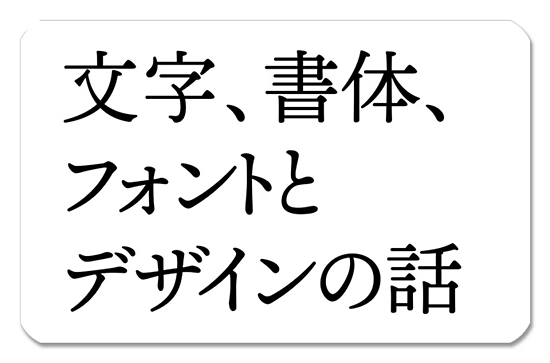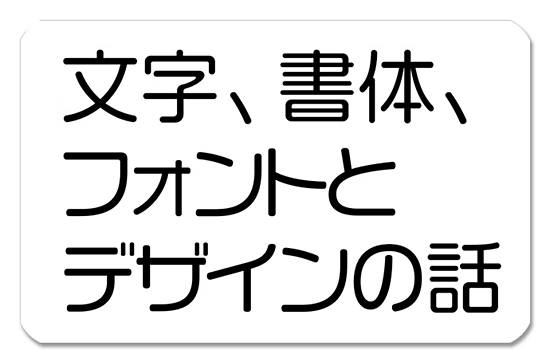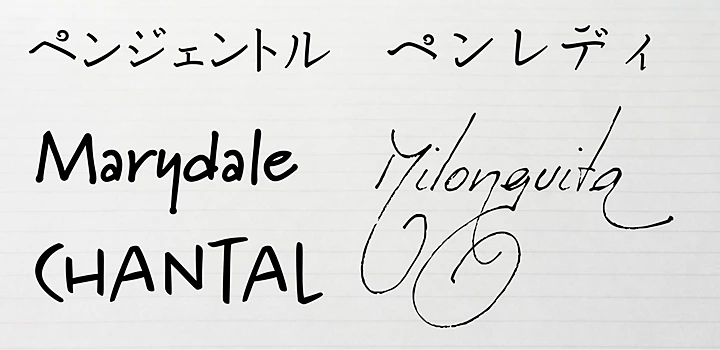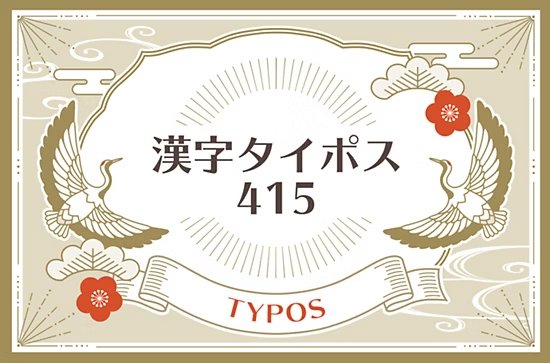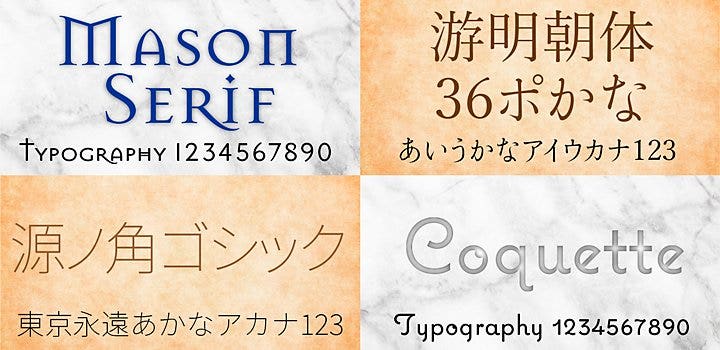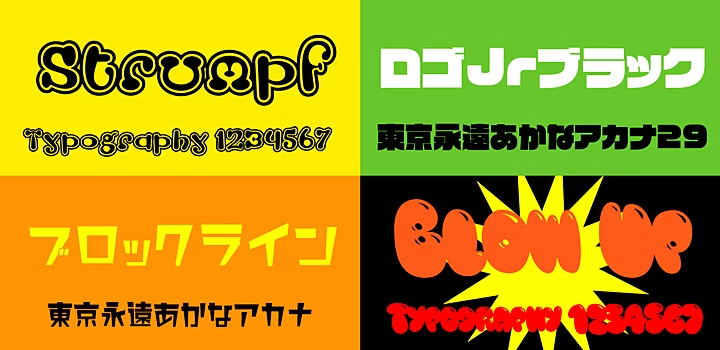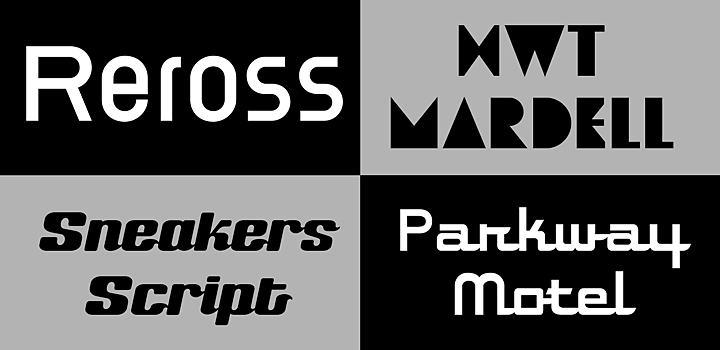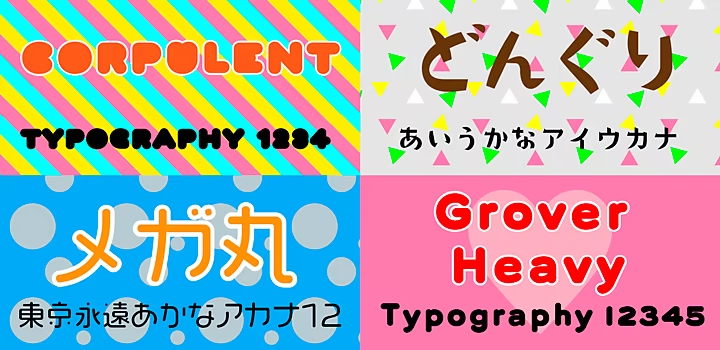
デザインイメージで決める!Adobe Fontsのおすすめフォント
たとえば同じ「あ」の文字でも、そのかたちとデザインはフォントによって大きく変わります。
デザインをする際には、かわいいデザインにしたい、かっこいいデザインに仕上げたいと言ったイメージや、伝える目的にあったフォントを選択し、レイアウトをしていくことが大切です。
ここではフォントによってデザインに与えるイメージはどう変わるのか、目指すデザインイメージを表現するためにはどんなフォントが最適なのかをご紹介します。
フォントはデザインイメージを決める大事な要素
デザインのイメージは、文字、写真・イラスト、レイアウト、配色等さまざまな要素が絡み合って作られていきます。
なかでも文字は情報を伝えるという大きな役割を持っているため、読みやすさ、見やすさを考えながらデザインに組み込むことが何よりも大切です。同時に、文字そのものがどのようなかたちで、どのような配置なのかによって、その伝わり方は大きく変わります。
たとえばこの2つの例を見たとき、どのような印象を受けるでしょうか。
左の例からは真面目でしっかりとした印象、右の例からは親しみやすく楽しそうな印象を受けるのではないでしょうか。 同じ文章であっても、選ぶフォントによって伝わり方は大きく変わることがわかるでしょう。
以降は表現したいデザインイメージごとに、Adobe Fontsで使えるものを中心にフォントを紹介していきます。
ポップなデザインに使えるフォント
ポップな印象にしたいとき、落ち着きのあるベーシックな明朝体やゴシック体よりはいわゆるデザイン書体を選ぶようにするとよいでしょう。
デザイン書体と言われるフォントの中にも非常に多くの種類があるので、この中から動きのある骨格を持つフォントや、画線の処理がユニークなフォントを選ぶのがおすすめです。
そのうえで、AdobePhotoshopやAdobe Illustrator、Adobe InDesign上で明るい色にする、フチ文字にする、加工を加えてみる、イラストと組み合わせてみるなどの装飾を加えていくことで、よりポップな印象に仕上げることができます。
ポップな文字のデザイン例:Strumpf/VDL ロゴJrブラック BK/ブロックライン/Blow Up
かわいいデザインに使えるフォント
かわいいデザインに仕上げたいときは、丸みのあるラインを持つものや、装飾的な処理がされているフォントを選ぶようにするとよいでしょう。
そのうえでカラフルな配色にしたり、テクスチャを加えていくことでさらにキュートに、かわいらしい印象に仕上げていくこともできます。
フォントによっては極端な処理によってその文字と認識しにくいものもありますので、文字情報として読みにくくなっていないか、きちんと確認をしましょう。
かわいい文字のデザイン例:Corpulent/どんぐり/VDL メガ丸/Grover Heavy
クールなデザインに使えるフォント
クールなデザイン、かっこいいデザインに仕上げたいときには欧文フォントをうまく活用してみましょう。
Adobe Fontsには非常に多くの欧文フォントが用意されているので、ベーシックなセリフ体、サンセリフ体、スラブセリフ体だけでなく、さまざまなデザインフォントが見つかるはずです。
フォントのセレクトとあわせて、落ち着いた配色にすることでよりクールな印象に仕上げることができます。
おしゃれなデザインに使えるフォント
おしゃれなデザイン、エレガントな印象に仕上げたいときにはどのような書体を選べばいいのでしょうか。
例えば日本語フォントでは、伸びやかな明朝体や細いゴシック体がおすすめです。欧文フォントではコントラストの強いセリフ体やスクリプト体を使うと上品な印象になります。また図のような装飾的な処理をした書体を使ってもよいでしょう。
文字から受ける印象はどのような文字の並びなのかによっても大きく変わります。Adobe Fontsでフォントを探す場合には、フォントを適用したい文字列をサンプルに指定するとよりスムーズに最適なフォントを選ぶことができるでしょう。
おしゃれな文字のデザイン例:Mason Serif/游明朝体36ポかな/源ノ角ゴシック/Coquette
レトロなデザインに使えるフォント
レトロなデザイン、クラシックなデザインに仕上げるには、日本語の場合は活字時代、写植時代の文字を復刻したフォントや筆書体フォントなどがよく使われます。直線的なフォントや一文字一文字が大きい(字面が大きい)フォントは現代的な印象を与える一方、筆の抑揚が強いものやかなが小さいものはクラシックな印象を与えます。
漢字タイポス
Trajan
欧文の場合はトラディショナルなフォントを選べばクラシックな印象になりますが、よりレトロな印象に仕上げたい場合にはデザイン書体も活用するとよいでしょう。
漢字タイポス
Boucherie Block
フレンドリーなデザインに使える手書き風フォント
親しみやすい、フレンドリーなデザインに仕上げるには、手書き系のフォントがおすすめです。
手書き系フォントにもペンで書いた文字やマーカーで書いた文字、鉛筆で書いた文字などさまざまな種類があります。
広告デザインではよりやさしい印象、あたたかい印象にするために、実際に手で書いた文字を画像(またはパス化)して使うこともあります。表現したいデザイン、目的に合わせてうまく使い分けるとよいでしょう。
フレンドリーな文字のデザイン例:ペンジェントル/ペンレディ/Marydale/Milonguita/Chantal